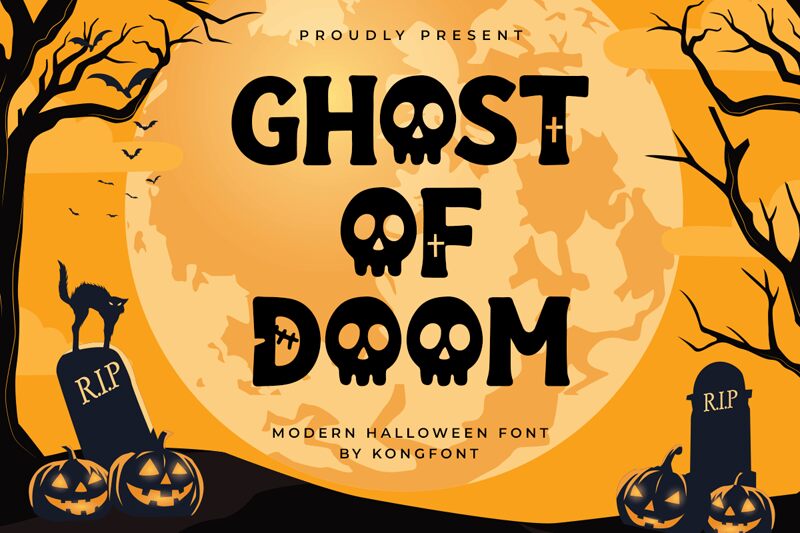
Ghost of Doom, creada por Kong Font, es una tipografía gratuita para Halloween que destaca por sus letras redondeadas y gruesas. Con un acabado suave, similar a un recorte, posee un aire de dibujos animados espeluznantes. Sus letras están estrechamente unidas, con espacios internos abiertos y terminaciones romas e irregulares que le dan un aspecto simpático, evitando ser demasiado agresiva o gótica.
Ghost of Doom funciona de maravilla en carteles de Halloween, invitaciones a fiestas, carteles de truco o trato, packaging de temporada y gráficos para redes sociales, ya que sus formas resultan festivas y un poco traviesas a primera vista. Esta fuente gratuita también es ideal para títulos de folletos, pegatinas y logotipos decorativos que busquen un estilo lúdico y artesanal para una temática de terror.